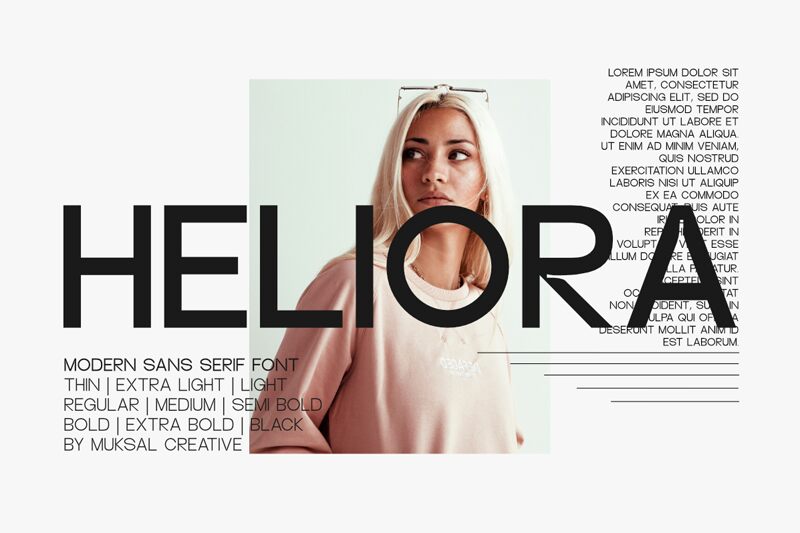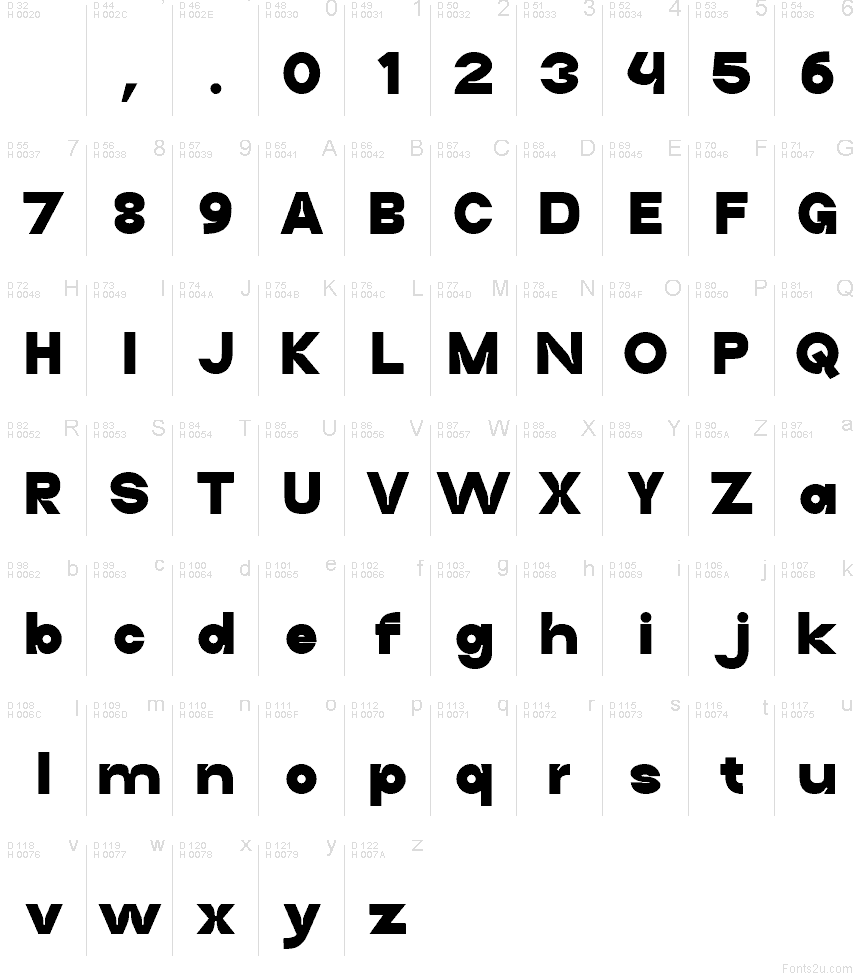
Heliora Black
Heliora Black von Muksal Creative ist eine kostenlose geometrische Sans-Serif-Schrift mit abgerundeten, großzügigen Formen und einem schlichten, kompakten Aufbau. Die breiten, kreisförmigen Rundungen und die geraden, kantigen Seiten verleihen den Buchstaben einen soliden, grafischen Rhythmus ohne überflüssige Details.
Heliora Black eignet sich hervorragend für Logodesigns, Plakattitel, Verpackungen, Event-Banner und kurze Web-Überschriften, da die Formen auch in großen Größen klar und ausdrucksstark bleiben. Diese kostenlose Schrift ist zudem ideal für Branding-Systeme und Social-Media-Grafiken, wenn du eine starke Sans-Serif suchst, die direkt, kompakt und vielseitig einsetzbar ist.